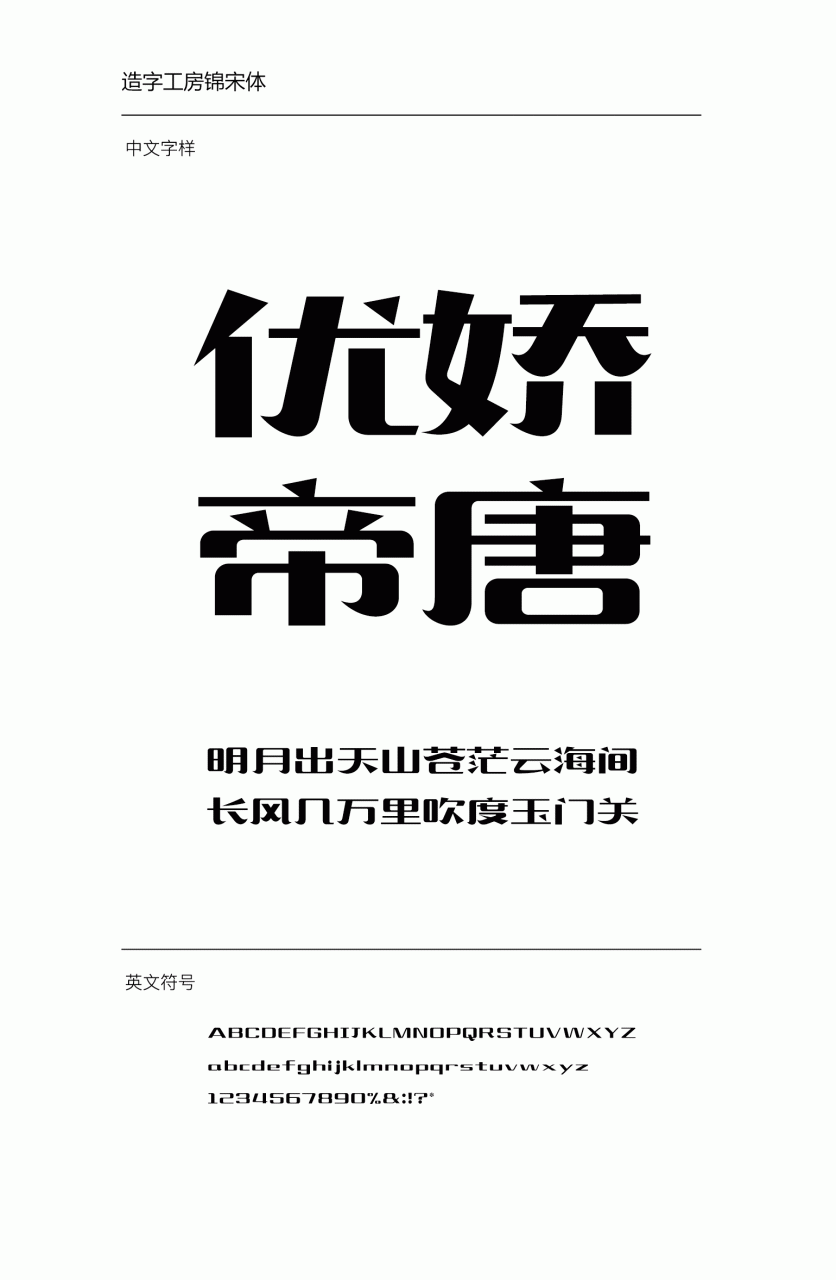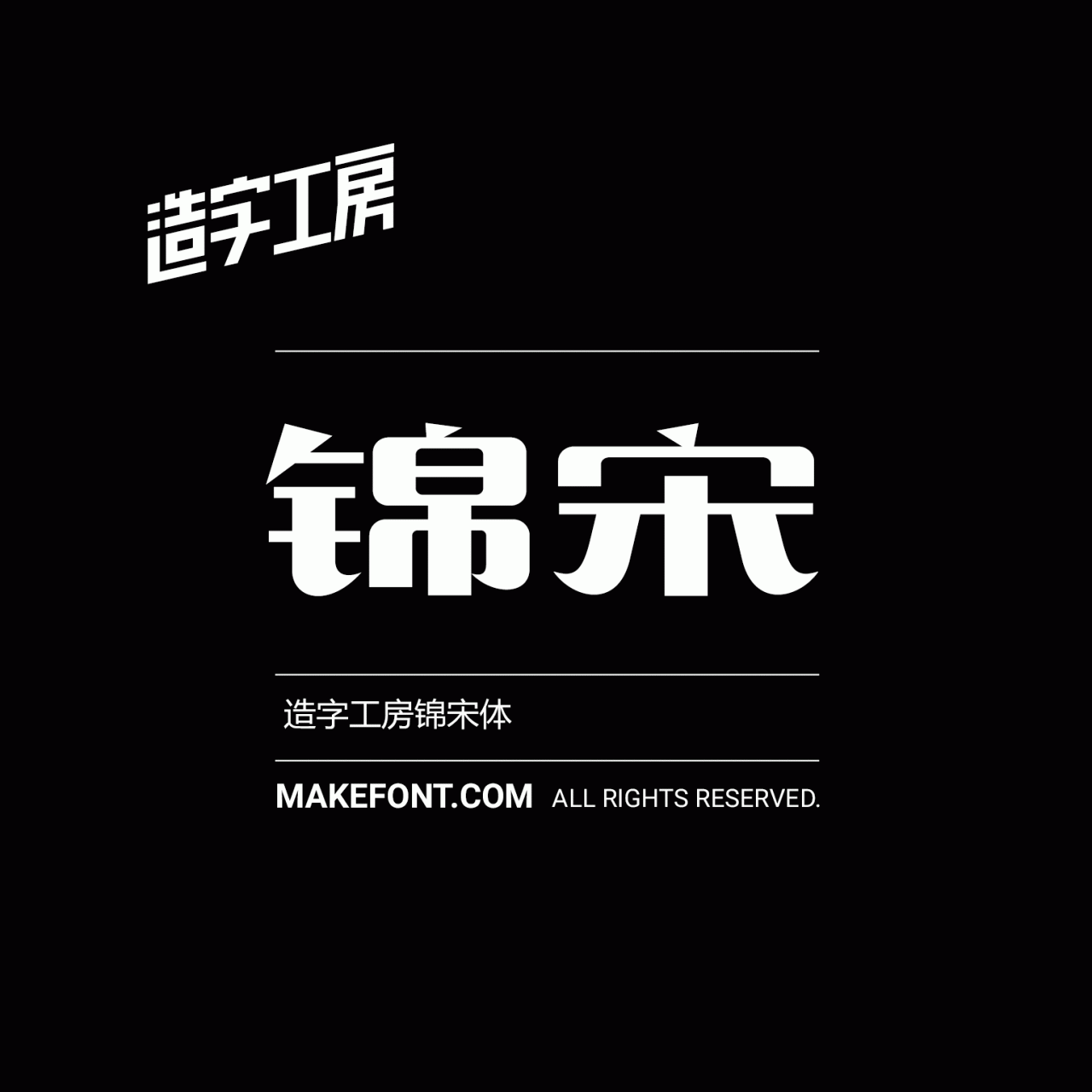
造字工房锦宋常规体设计说明
造字工房锦宋体笔画简洁、笔锋柔和典雅,曲线舒展,勾画处理部分如新月牙,点、提尖角跟撇的圆润处理相互呼应,刚柔并济、工整而不失精巧,最大程度的展现笔画的柔和秀美,浓笔重彩,有极强的视觉表现力。适用于大标题及个性品牌设计推广等环境。本字体为简体字库,采用OpenType/CID格式,Adobe-GB1-5编码。基于中华人民共和国GB2312-80字符集标准,另按需添加101个汉字。共收容字数6864CJK汉字,ASCII常用字符100个。